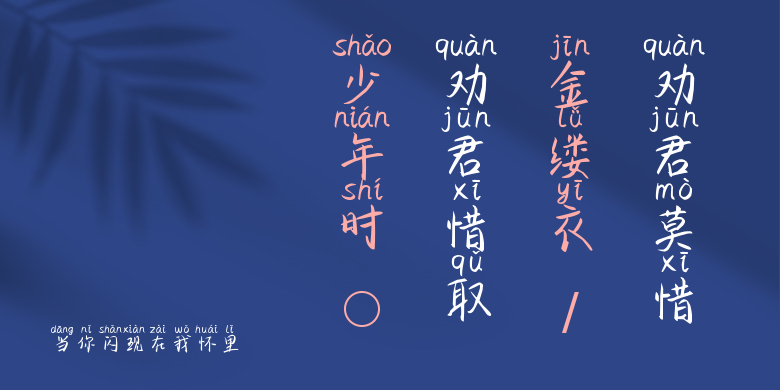
当你闪现在我怀里
当你闪现在我怀里,这款字体结构工整、笔画清晰,兼顾美观与易读性,适用于标题、正文、海报、包装、LOGO 等多种场景。字形优雅稳定,风格百搭耐看,适配日常排版与创意设计,让文字呈现更舒适、更具质感。当你闪现在我怀里一笔一画,皆是细节,以均衡的比例、流畅的线条打造舒适视觉体验,字形端正大气,风格简约现代。无论是商业设计、品牌宣传还是日常排版,都能轻松驾驭,让文字更有格调与力量。当你闪现在我怀里字体下载。